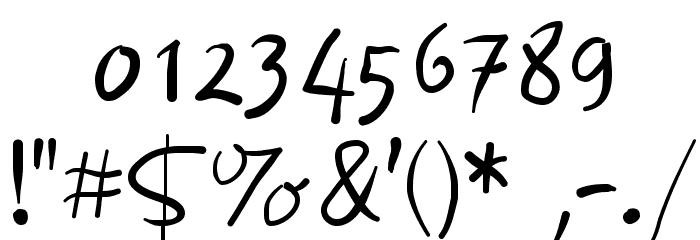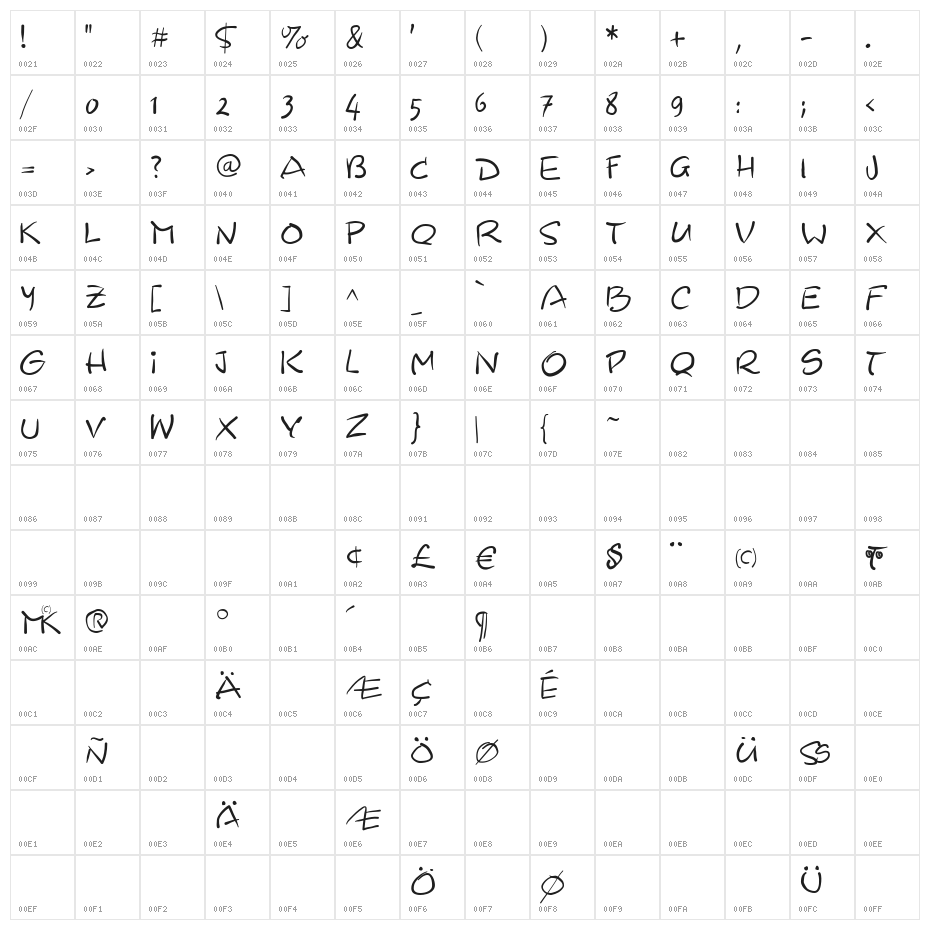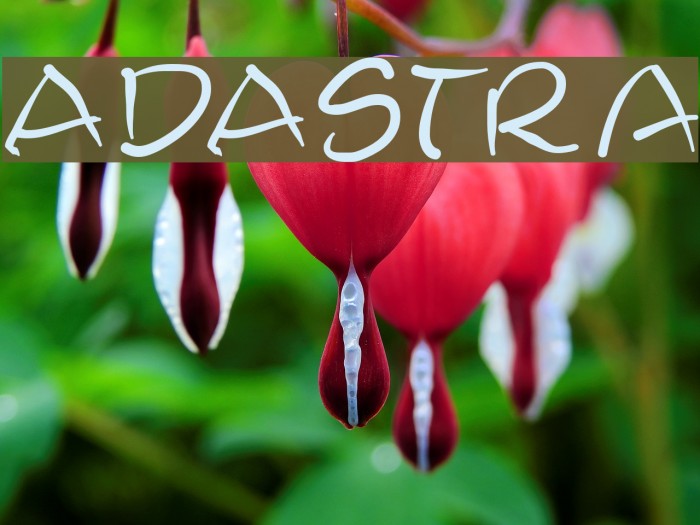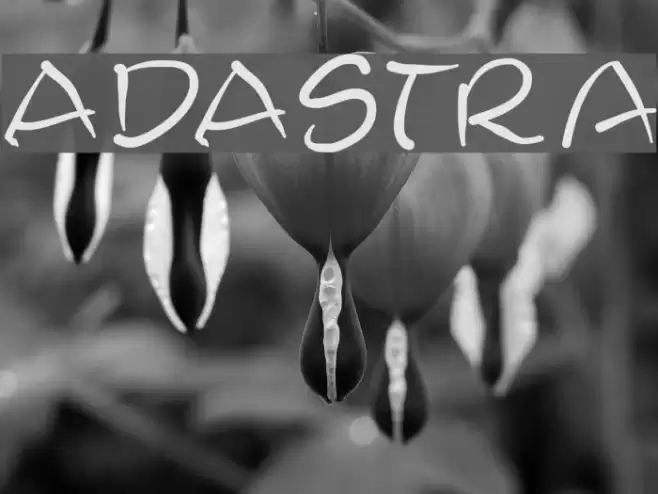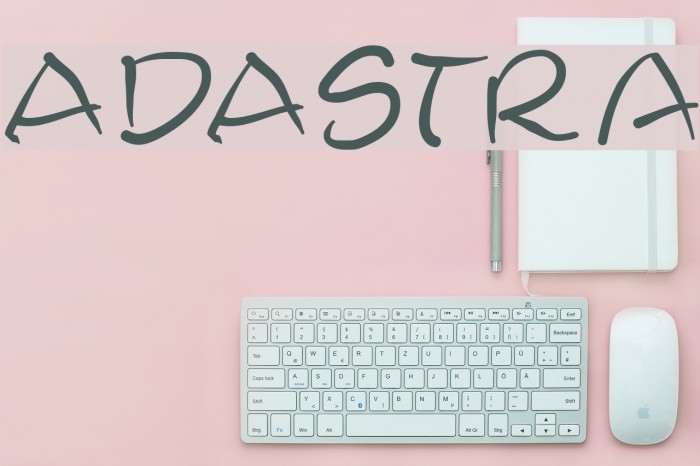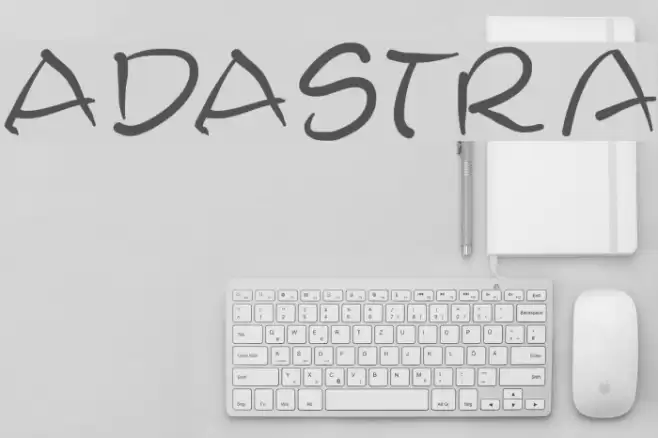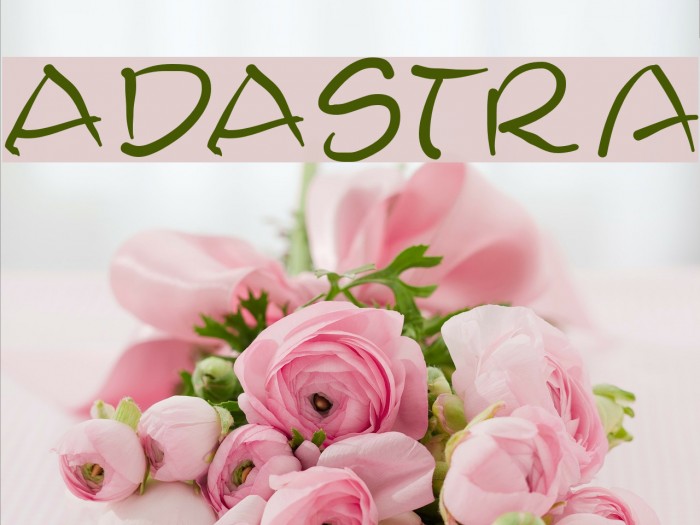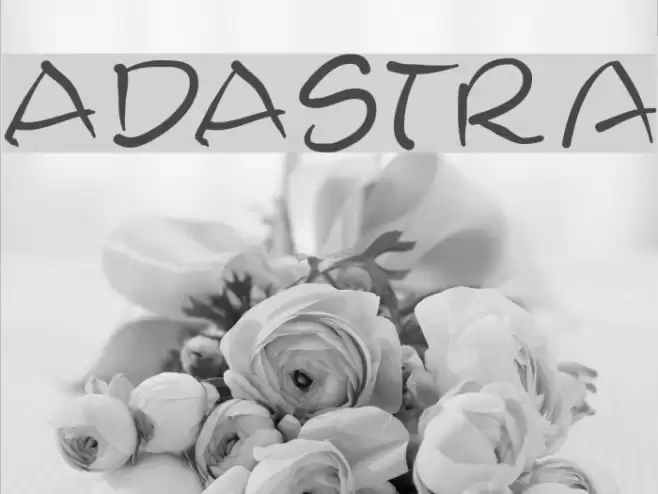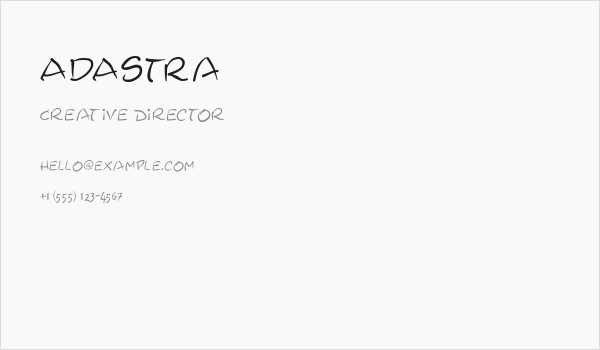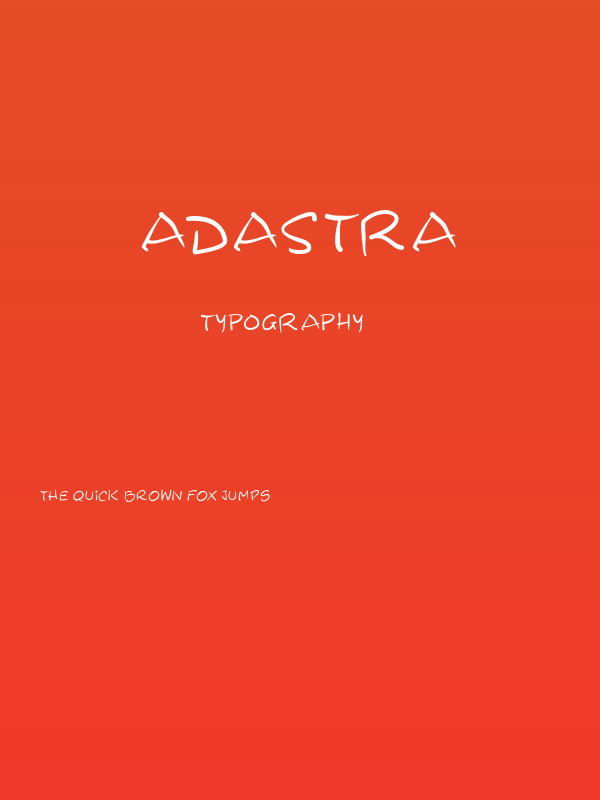
AdAstra Font
| Caz de utilizare | Logos, Invitations, Greeting Cards |
| Proiecte propuse | Ideal for greeting cards, invitations, personal branding, and creative projects that require a friendly and informal touch. |